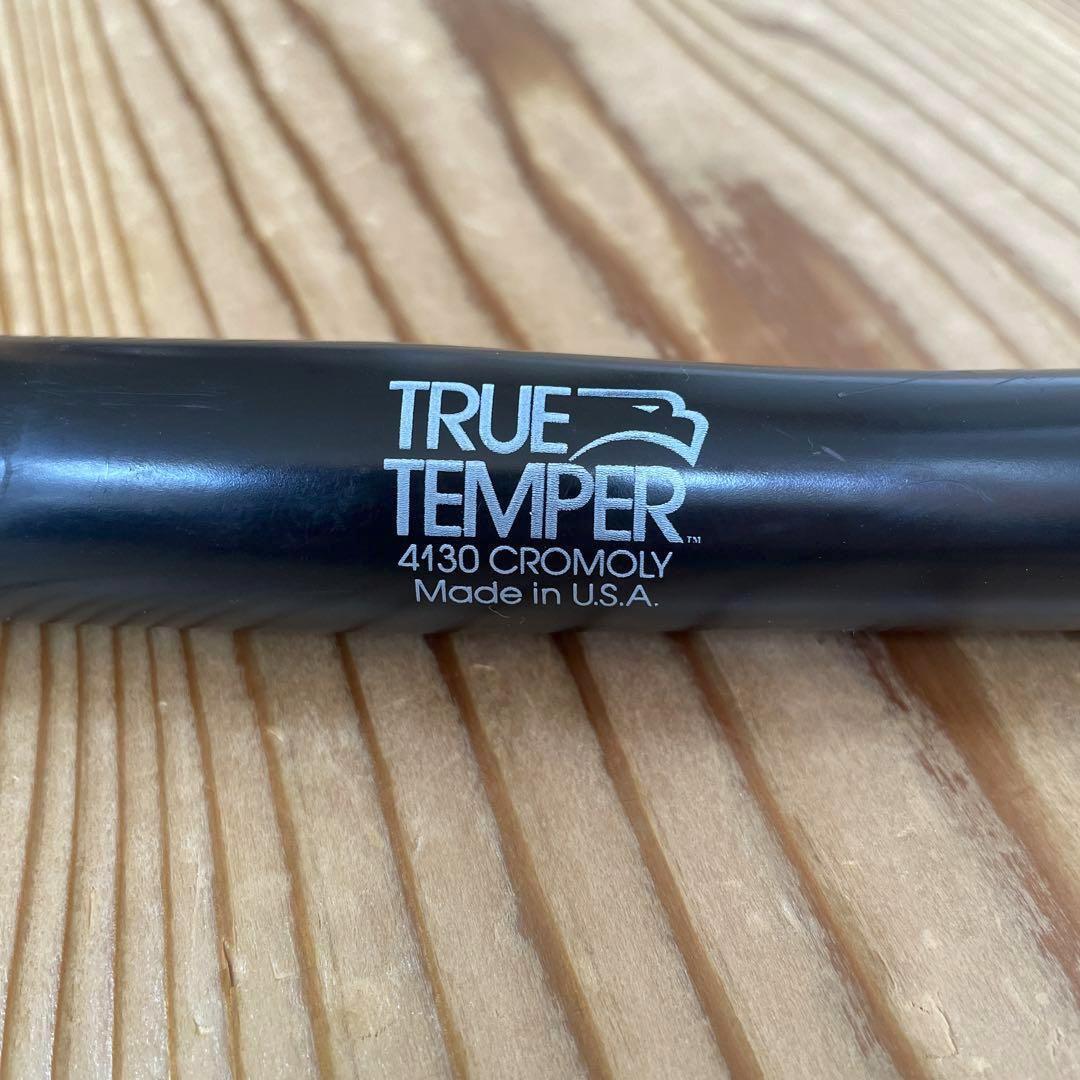
Schriftartsuche der Wortmarke »True Temper« aus den 1990er Jahren
Hallo, ich benötige Hilfe bei der Identifizierung der verwendeten Schrift(en). Es handelt sich um die Wortmarke eines US-amerikanischen Stahlherstellers – hier jetzt auf einem vintage MTB-Lenker. Es ist das "alte" Logo aus den 1990er Jahren. Vielen Dank!
die etwas spezielle »1« hatte mich (als Laien) bereits irritiert und war wahrscheinlich die Ursache, weshalb ich über Schriftbestimmmungsseiten nicht weitergekommen bin. Perfekt, danke!